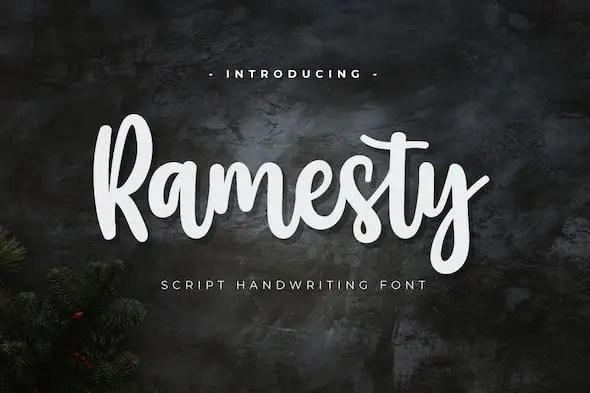
Ramesty Script Font – Fonte Grátis
Ramesty Script Font
A Ramesty Script Font é uma seleção única de fontes que se destacam por seu encanto e elegância nas escritas manuscritas. É perfeita para todas as criações que buscam um toque autêntico e pessoal, como logotipos, editoriais e designs gráficos. Combinada com o designer twinletter, essa fonte oferece uma experiência de design única, tornando cada projeto mais personalizado e atraente sem precisar usar imagens ou recursos de textura adicionais. Seja para criar cartões de aniversário, logotipos empresariais ou até mesmo designs de páginas da web, você pode adicionar um toque único e autêntico à sua obra com a Ramesty Script Font, criando uma experiência visual que se destaca no meio do design gráfico.